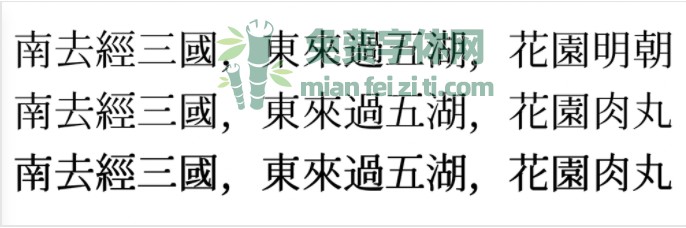
花园肉丸:游走于古典与可爱之间的字体免费商用字体资讯
花园肉丸字体是使用“狮尾肉丸”字体的转换程序,套用到“花园明朝”字体后得出的字体,发现效果还挺不错的的。花园肉丸字体基于花园明朝的转角的三角形转成半圆形改造,是一款游走于古典与可爱之间的字体。欢迎大家自由应用、自由优化、自由改作!
附注:花园肉丸的Regular字重,是直接来自花园明朝,而Medium字重是透过程序产生,不能确定所有的字都正常,可能某些字会转换失败。大家在使用的时候请检查一下哦。
花园明朝与花园肉丸的对比